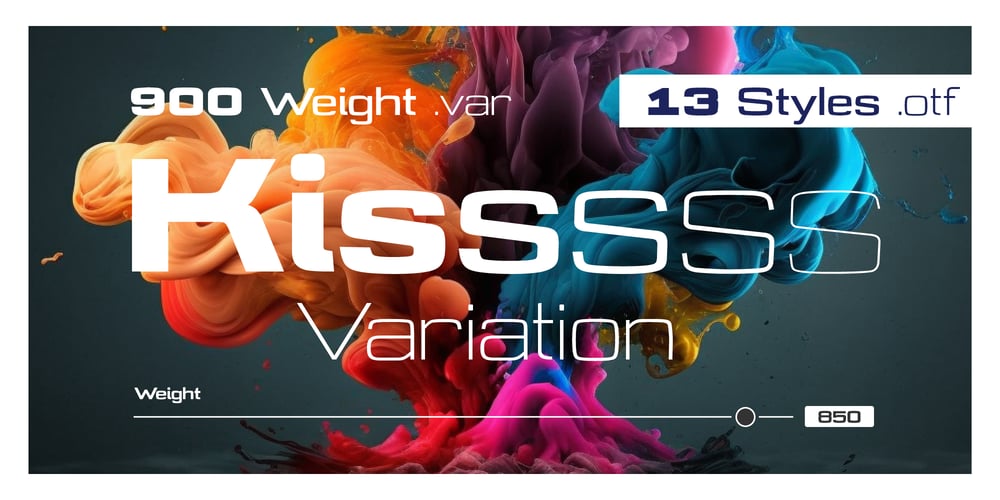
Millenium Pro Var Font Family was designed by patrice provost and published by TypoStudio Pro. Millenium Pro Var contains 1 styles and family package options. La famille Millenium est composée de modèles dont le poids varie progressivement. Elle est très étendue. Elle va de “Super Thin” à “Extra Black”. Unique au monde, sa finesse permet de concevoir un style très léger même pour l’impression d’affiches et d’autres grands formats. Conçu dès l’origine comme un caractère variable, le Millenium offre une gamme de 900 variations possibles et une infinité de créations…